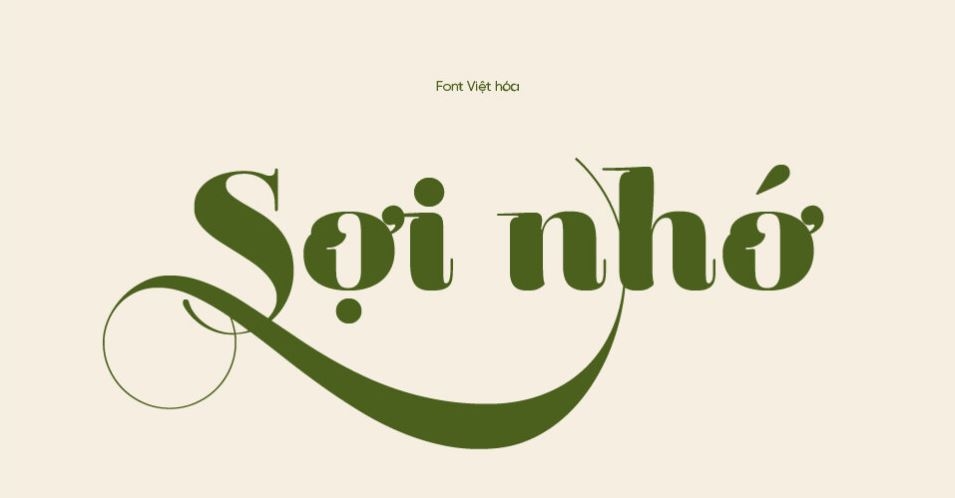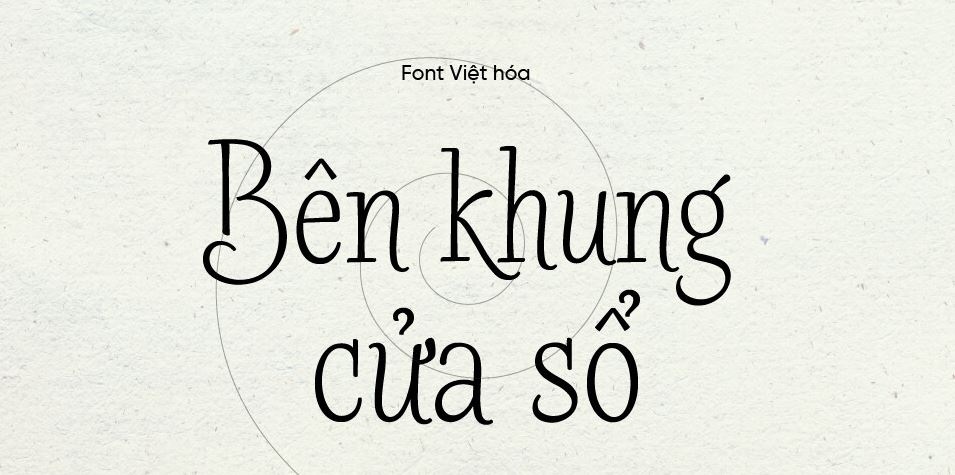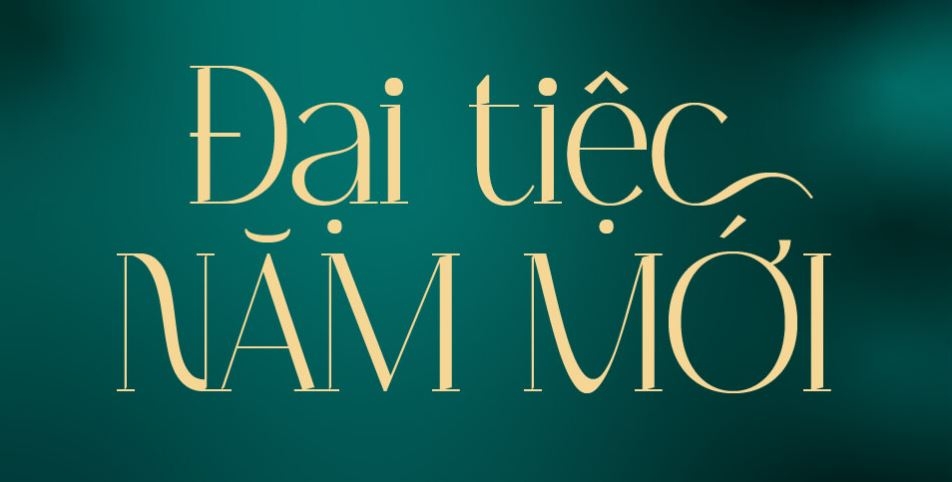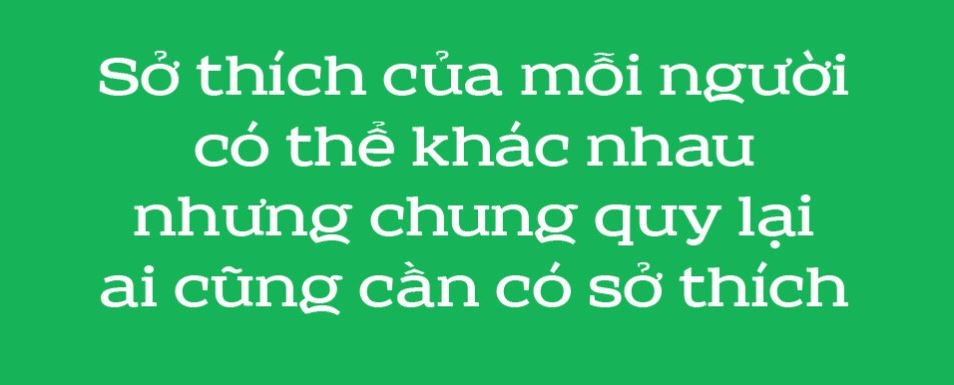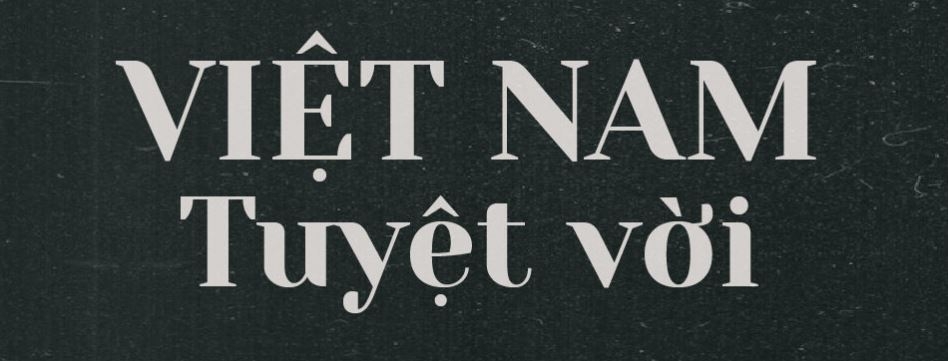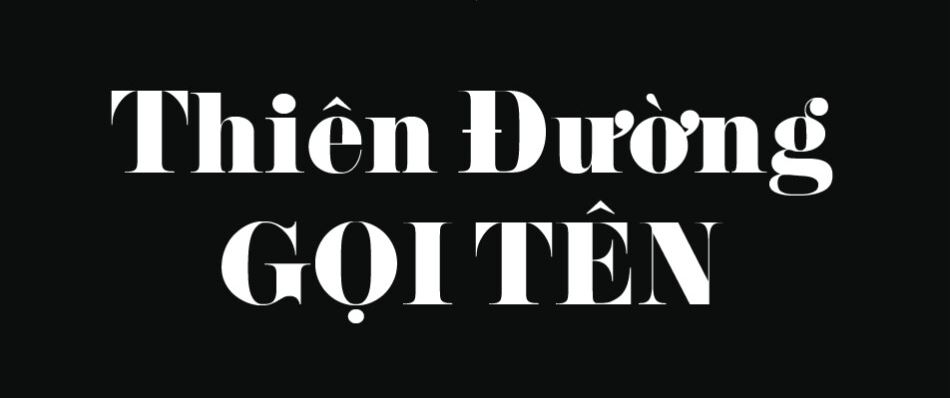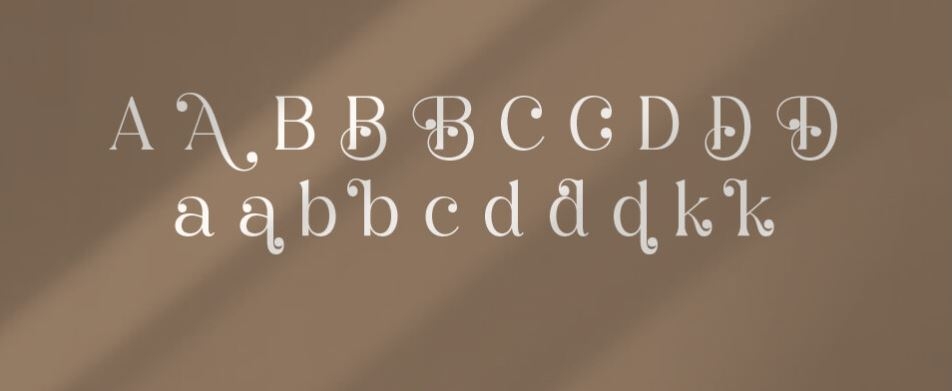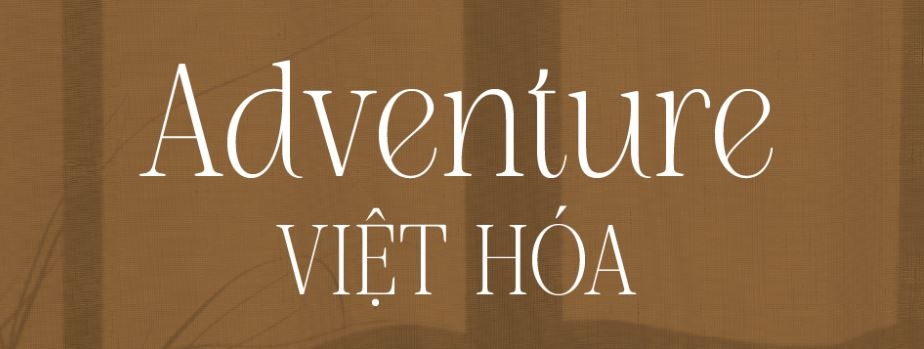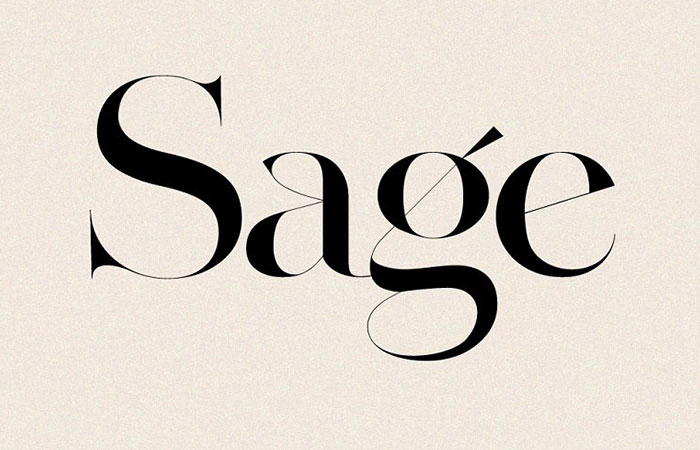
Tổng hợp 15 font serif đẹp hiện nay
Mang đậm nét cổ điển và vẻ đẹp sang trọng, font chữ có chân luôn là lựa chọn ưu tiên của giới thiết kế, thu hút ánh nhìn ngay từ cái nhìn đầu tiên. Trong bài viết này, chúng tôi sẽ giới thiệu đến bạn 15 font  serif và ấn tượng, được nhiều người tin dùng.
Font serif là gì?
Font serif là loại phông chữ có các đường chân hoặc nét nhỏ được thêm vào các chi tiết của chữ cái. Những đường nét này giúp tạo sự ổn định cho hình dạng chữ và mang lại cảm giác trang trọng, cổ điển cho văn bản. Nhờ đặc điểm đó, font serif được sử dụng rộng rãi trong thiết kế website, quảng cáo, logo, cũng như trong các tài liệu văn phòng cần sự nghiêm túc và chuyên nghiệp.
15 mẫu font chữ có chân phổ biến nhất
Reina
Reina là một font serif dễ đọc với kích thước nhỏ gọn, giúp tối ưu không gian trong các tài liệu in ấn và kỹ thuật số. Điểm nổi bật của font này nằm ở sự tương phản rõ rệt giữa các nét chữ, giúp người đọc dễ dàng nhận diện từng ký tự. Với nhiều kiểu dáng đa dạng, từ đơn giản đến cầu kỳ, từ cổ điển đến hiện đại, Reina là lựa chọn lý tưởng cho thư pháp, thiết kế đồ họa, giao diện web hay ứng dụng di động.
Barmbrack
Lấy cảm hứng từ phong cách showcard lettering, font serif Barmbrack sở hữu những đường nét đậm, phóng khoáng cùng phần chân chữ được cách điệu sinh động. Nét chữ dày dặn mang lại cảm giác mạnh mẽ, kết hợp cùng các đường gạch chân biến hóa tạo nên vẻ vui tươi và độc đáo. Đây là lựa chọn hoàn hảo cho tiêu đề website, poster quảng cáo hay bất kỳ thiết kế nào cần thu hút sự chú ý ngay lập tức.
Tropical Qebalon
Tropical Qebalon mang đến cảm giác mềm mại và tinh tế qua từng đường nét. Sự thay đổi linh hoạt giữa các nét dày và mảnh tạo nên phong cách lãng mạn pha chút hoài cổ. Với vẻ ngoài mượt mà và đầy cá tính, font serif này rất thích hợp cho các dự án sáng tạo, nghệ thuật, thiết kế cá nhân hóa hay typography nghệ thuật.
Sreda
Sreda nổi bật với nét chữ đậm và mạnh mẽ hơn so với nhiều font serif khác. Chân chữ được thiết kế dày và chắc chắn, tạo cảm giác vững chãi và đáng tin cậy. Font này rất hiệu quả khi dùng cho tiêu đề, banner hoặc những đoạn văn bản cần nhấn mạnh trong thiết kế chuyên nghiệp.
Yeseva One
Yeseva One sở hữu đường nét mảnh mai, mang lại cảm giác cổ điển và thanh lịch. Các đường cong được chăm chút tỉ mỉ khiến tổng thể chữ trông quý phái và tinh tế. Với phần chân chữ được cách điệu đầy tự do, font này rất phù hợp với các dự án thiết kế như thiệp cưới, bìa sách, logo hoặc ứng dụng nghệ thuật.
Pistilli
Pistilli ghi dấu ấn với những đường nét tinh tế và sang trọng. Chân chữ thanh mảnh, sắc sảo tạo nên cảm giác quý phái, rất phù hợp với những thiết kế yêu cầu sự trang nhã như quảng cáo cao cấp, thiệp cưới hay tiêu đề tạp chí thời trang.
Balerga
Balerga mang đậm phong cách cổ điển và cao cấp với bố cục chữ chắc chắn, đậm nét. Được thiết kế để truyền tải sự trang trọng và bền vững, font này lý tưởng cho tiêu đề lớn, ghi chú quan trọng, logo hoặc bất kỳ thiết kế nào cần tạo ấn tượng mạnh mẽ và chuyên nghiệp.
Adventure
Adventure là font serif với thiết kế đặc trưng ở các đường chân chữ rõ nét, gợi cảm giác mạo hiểm và mạnh mẽ. Đây là sự lựa chọn hoàn hảo cho các thiết kế liên quan đến chủ đề khám phá, phiêu lưu, thiên nhiên hoặc các hoạt động ngoài trời, mang đến tinh thần hành động và năng động cho thông điệp của bạn.
Font serif có thể xem là một công cụ mạnh mẽ trong việc truyền tải thông điệp một cách nhanh chóng và hiệu quả ngay từ cái nhìn đầu tiên. Mỗi kiểu chữ đều mang trong mình những đặc điểm riêng biệt, góp phần thể hiện cá tính và phong cách của nội dung. Hy vọng rằng danh sách các font serif được giới thiệu trên đây sẽ trở thành nguồn cảm hứng hữu ích cho bạn trong quá trình xây dựng các chiến dịch thiết kế và truyền thông ấn tượng.